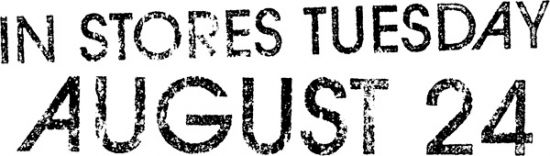
Suche Schrift von Marble Index (Rockband)
Ich suche die Schrift aus dem angehängten Beispiel. Die Original-Schrift selber ist sicherlich nicht "kaputt". Ich weiss blos nicht wie sie heißt. Dürfte eigentlich nicht so schwer zu finden sein mit dem "A" aber ich hab mir schon einen Wolf gesucht und sie nicht gefunden.
Schriftbeispiel:
Ohne nachzusehen: Ist das nicht Herb Lubalins Avant Garde, mit dem A aus dem Ligaturenset? Bitte korrigieren, falls ich falsch liege.
Ligaturenset... da hätte ich auch selber drauf kommen können...